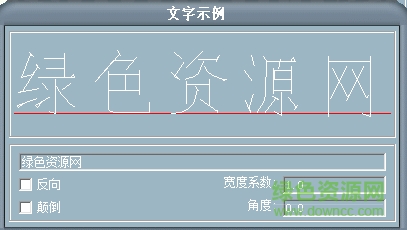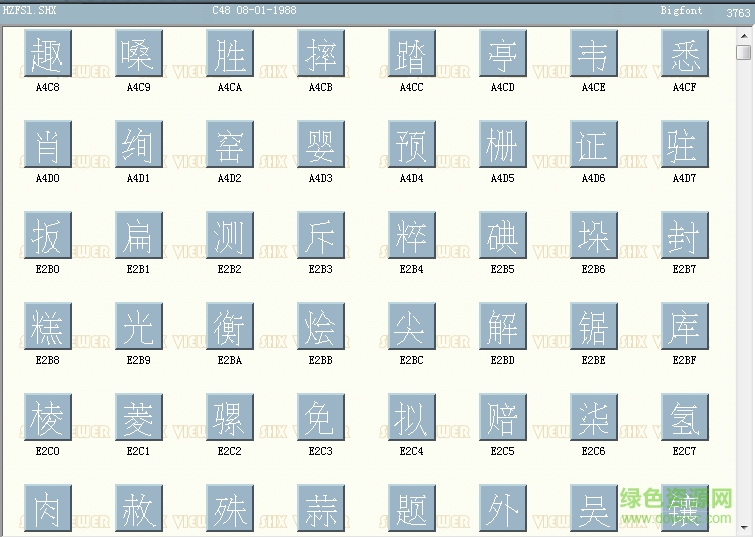
hzfsl.shx字體
hzfsl.shx字體是一款cad制圖軟件專用的字體應(yīng)用,是一款字型優(yōu)美的宋體字體,字體支持多種輸入法輸入顯示,能有效顯示圖紙信息,現(xiàn)在來(lái)綠色資源網(wǎng)下載,按下方提示安裝就能使用了!
hzfsl.shx字體簡(jiǎn)介
hzfsl.shx字體是一款用于cad軟件的字體應(yīng)用,屬于autocad雙線仿宋簡(jiǎn)體中文字體,很多cad圖紙?jiān)谠O(shè)計(jì)的時(shí)候會(huì)用到此字體,如果使用了,那在閱讀相應(yīng)的圖紙的時(shí)候也就需要安裝該字體才能正常的看圖紙